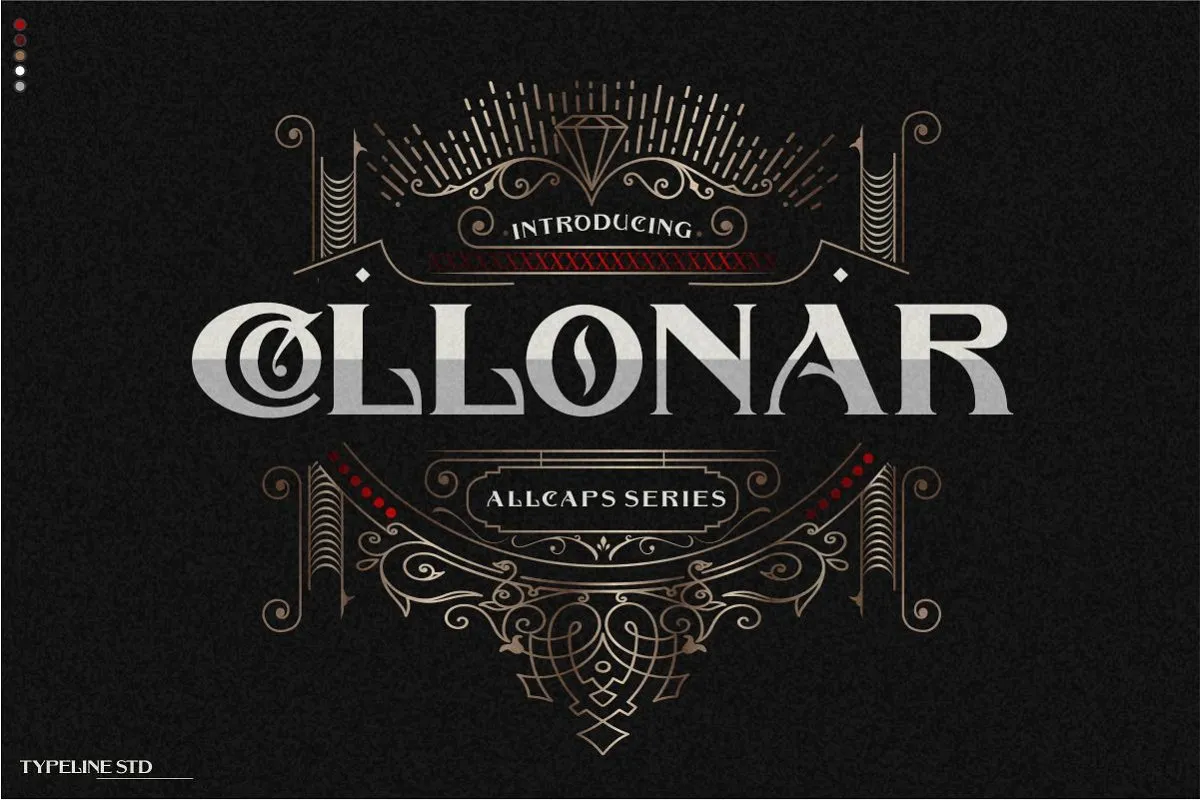
Collonar Typeface – Download Grátis
Aqui está uma breve descrição para a página de download da fonte ‘Collonar Typeface’ em português do Brasil: Olá font lovers! Estamos muito felizes por ter um novo elemento para sua paleta de personalização, chamado Collonar Typeface. Este é um tipo serif vintage que oferece um toque retro e moderno a seus projetos. Ideal para identidade visual, branding, design de interfaces de usuário (UX/UI), t-shirts, posters e qualquer projeto tradicional que deseje dar um tom clássico. Criado pelo designer Hamilton, este é um tipo fonte original vintage perfeito para aqueles que buscam uma aparência autêntica em seus trabalhos. Com sua aparência moderna e vintage clara, Collonar Typeface tem o poder de transformar qualquer design em algo especial, seja ao criar logomarcas, branding ou até mesmo rótulos de livros e revistas. Um dos destaques de Collonar é a presença constante de letras maiúsculas, que são usadas para criar um estilo moderno e notável. Hamilton criou uma função flexível que permite usar as letras maiúsculas tanto no sentido visual quanto em aplicações tipográficas. Isso lhe dá liberdade para explorar o máximo da capacidade de Collonar, tornando-o perfeito para qualquer projeto tradicional. Se você está procurando por um toque vintage sem perder a modernidade e uma fonte de alta qualidade, Collonar Typeface é definitivamente seu novo amigo. Experimente Collonar Typeface em seus próximos projetos e descubra o poder das letras seríferas vintage!